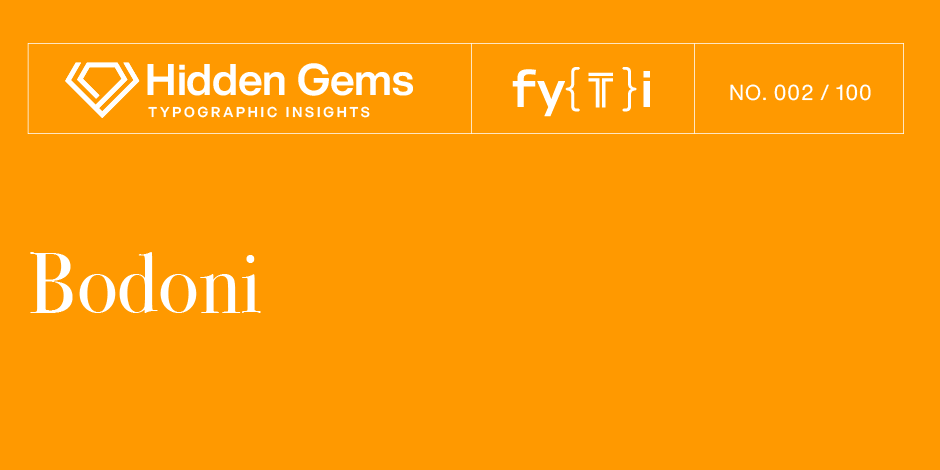
Gemmes cachées Bodoni™
FONDERIE : Bitstream, Linotype, International Typeface Corporation, Monotype, et plusieurs autres.
CONCEPTEUR : Giambattista Bodoni, et bien d'autres
CLASSIFICATION : Neoclassical Serif
POURQUOI BODONI
- Le fort contraste entre les traits épais et fins, les courbes raffinées et les empattements aigus de Bodoni créent un impact visuel saisissant.
- Le style typographique Bodoni est un élément essentiel de la communication graphique élégante. Il brille dans la conception éditoriale, l'image de marque et la publicité, évoquant un sens du luxe et de la tradition. Le savoir-faire méticuleux dont témoignent les lettres originales de Bodoni lui confère une place de choix parmi les classiques de la conception typographique.
ANCESTRY
- Conçus par Giambattista Bodoni à la fin du XVIIIe siècle, ses dessins ont été largement reproduits et interprétés à maintes reprises. Les dessins originaux de Bodoni restent toutefois difficiles à reproduire. En effet, Bodoni a créé plus de 140 polices romaines avec leurs homologues italiques, chacune présentant des caractéristiques de conception caractéristiques adaptées à différentes tailles et applications.
- Le premier renouveau moderne a été réalisé par Morris Fuller Benton pour l'American Type Founders Company (ATF) en 1910. Il s'est inspiré des meilleures qualités de l'œuvre imprimée de Bodoni. Cette reprise n'était pas une copie directe mais une interprétation du style distinctif de Bodoni.
- Les Polices produites au début du XXe siècle présentaient souvent des empattements durs qui s'écartaient des dessins plus doux et plus conviviaux de Bodoni - et capturaient rarement l'essence de ses italiques originaux. Les versions phototypiques ultérieures ont soit copié des polices en métal, soit tenté - sans grand succès - d'interpréter les dessins originaux de Bodoni.
- Récemment, de nouvelles interprétations de l'œuvre originale de Bodoni ont vu le jour chez International Typeface Corporation, Linotype et Monotype, marquant des avancées significatives dans la renaissance de son œuvre.
PAIRING BODONI
- Les caractères humanistes sans empattement tels que Frutiger® Suivante ou ITC Legacy® Sans constituent un excellent contrepoint visuel à Bodoni.
- Les sans géométriques, tels que Futura® Suivante et ITC Avant Garde Gothic, offrent également des contrastes dynamiques avec n'importe quelle police Bodoni.
- Les caractères à empattement peuvent également être de puissants partenaires d'association. Il suffit de penser à des dessins comme ITC Charter® et Neue Swift®.
FAITS CLASSIQUES
- Bodoni confia un jour à un ami qu'il avait agonisé plus de six mois et produit des milliers d'épreuves d'essai pour choisir le bon caractère pour la page de titre de l'un de ses livres !
- Giambattista Bodoni était manifestement un perfectionniste, mais il était aussi pragmatique. Les recherches effectuées sur ses poinçons métalliques originaux révèlent qu'il a utilisé le poinçon du chiffre 6, à l'envers, pour produire le caractère du chiffre 9. Les dessinateurs de caractères actuels savent qu'il s'agit de deux caractères différents, avec des différences subtiles de poids de trait.